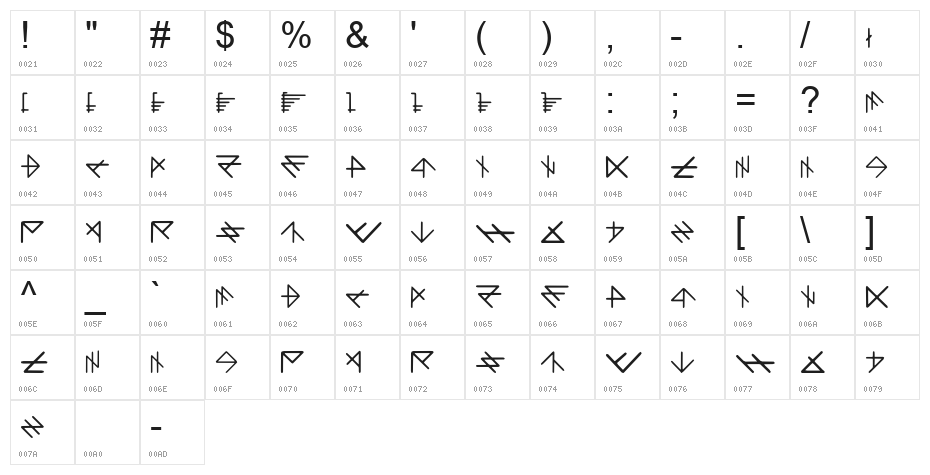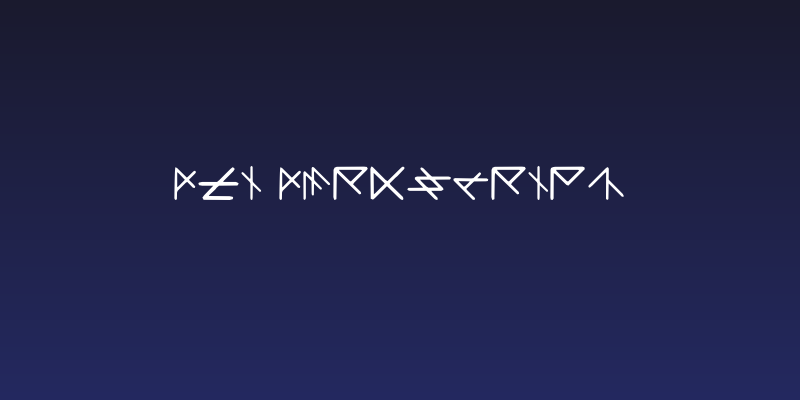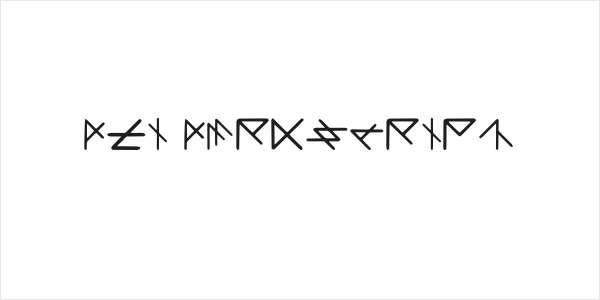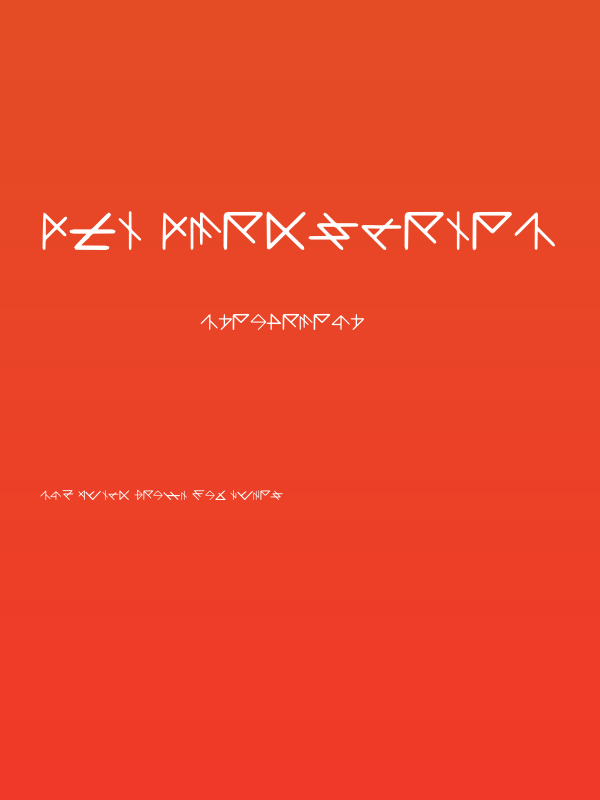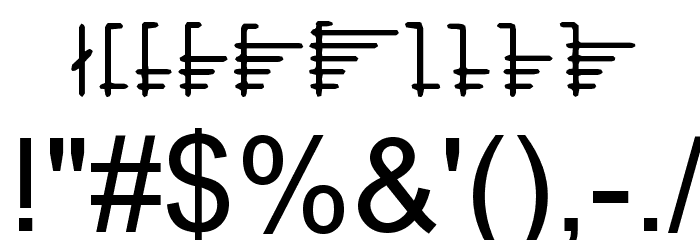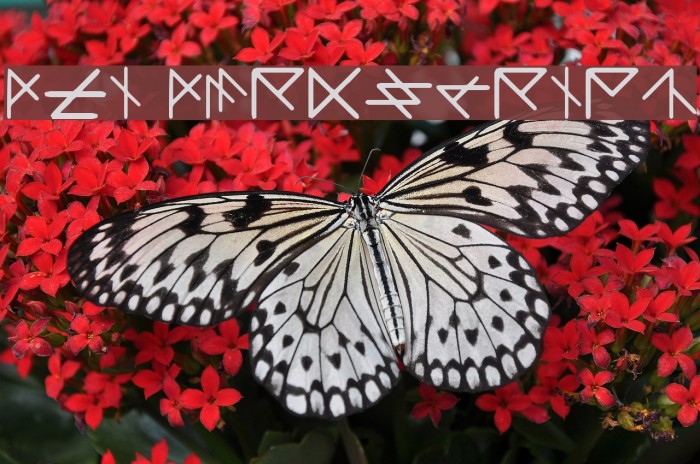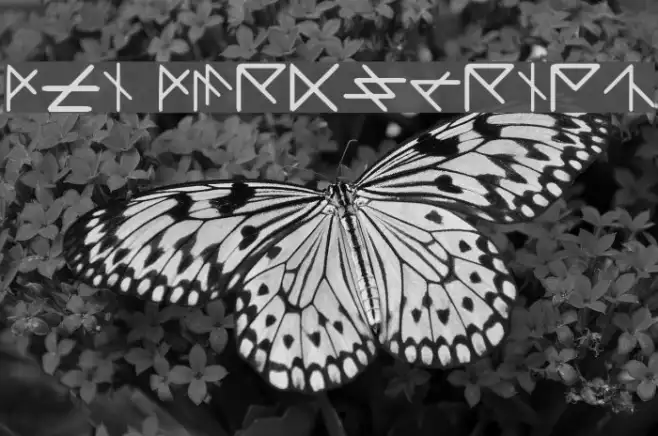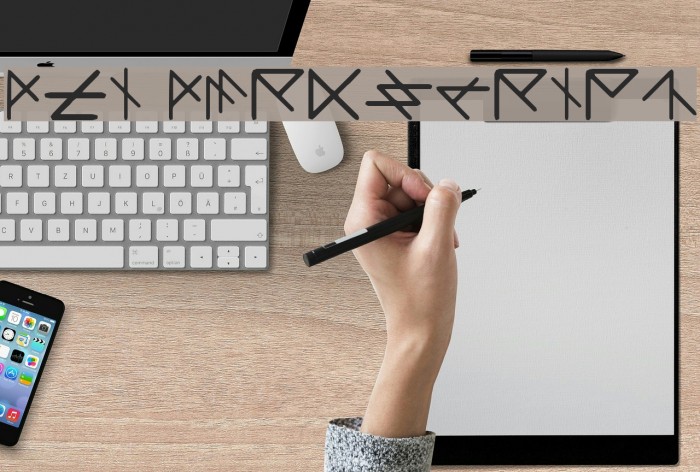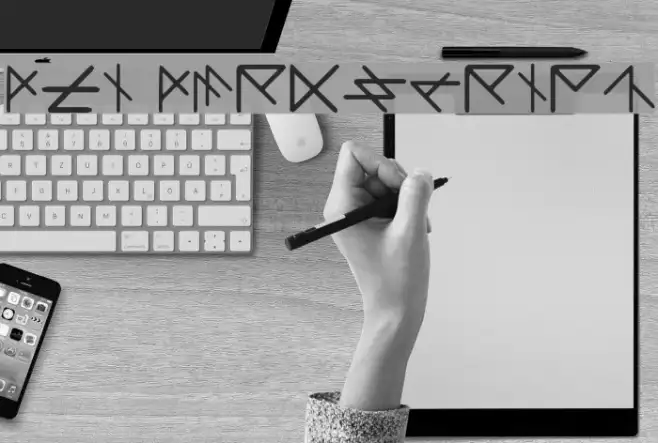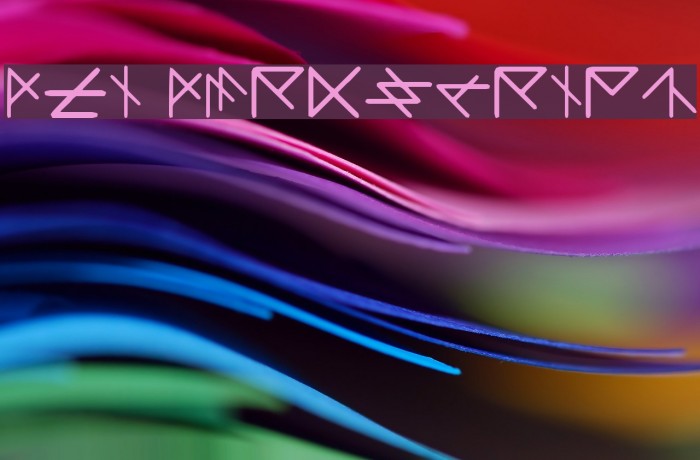
DLI DarkScript Font
| Estilo general | Mystical, Ancient, Geometric |
| Caso de uso | Logos, Posters, Themed Events |
| Proyectos propuestos | Ideal for fantasy-themed designs, video game interfaces, or branding that requires a mystical or ancient touch. |